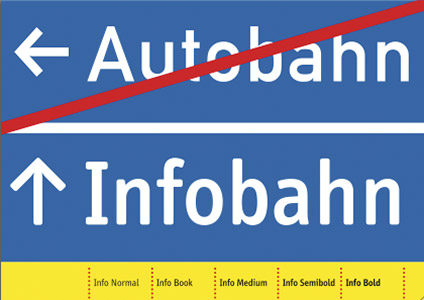
Sammelkarte: German InfobahnEine Fontcard vom März 1996, gestaltet von Erik Spiekermann.
Sie zeigt seine neue FF Info, entworfen für das Leitsystem des
Flughafen Düsseldorf. Er stellt sie neben die deutsche Autobahnschrift DIN
und fragt: Autobahn oder Infobahn? Die Karte offenbart unmittelbar die
Schwächen der alten DIN-Schrift und die Stärke von FF Info. Weiterlesen ...
![]() Mit dem Erscheinen der Karte stand noch nicht fest, dass es mal eine
Text-Variante zur FF Info geben wird. Die Display-Version
entwarfen Erik Spiekermann und Ole Schäfer bei MetaDesign.
Sie war die Basis des neuen Leitsystem, das MetaDesign für den Düsseldorfer Flughafen konzipierte. Die
Stärken der FF Info: abgerundete Ecken (=Robustheit), enge Buchstabenformen
(= platzsparend), gut unterscheidbare Buchstaben (= beste Lesbarkeit für
internationales Publikum) und eine kräftige Strichstärke. Richtig
zugerichtet beansprucht FF Info rund 85 % des Raums der DIN-Schrift, bei
deutlich besserer
Lesbarkeit.